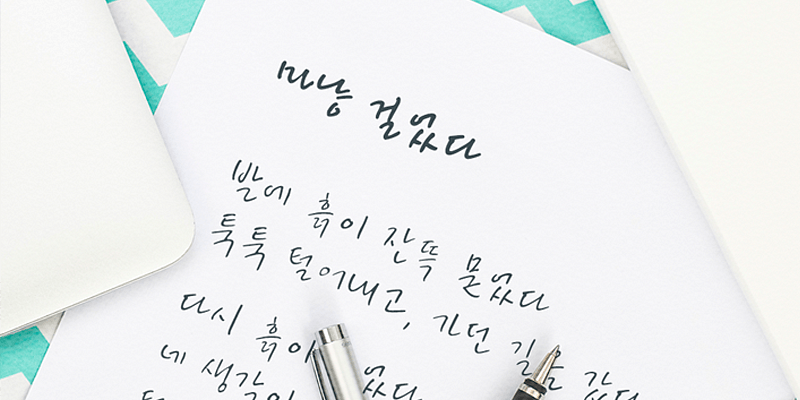
Sandoll 02는 자유롭고 캐주얼한 느낌을 주는 필기체입니다. DanA 글꼴로 유명한 손영희씨는 이 글꼴이 주는 자연 그대로의 감정을 강조합니다. 그리고 저녁이 되면 각 획의 두께로 자유분방한 느낌을 연출할 수 있습니다.
Sandoll(산돌)은 한국을 대표하는 글꼴 개발업체입니다. 약 40년 동안 거의 600개에 달하는 글꼴을 개발해 왔습니다. 이 개발업체는 한중일 개발, 한국어 및 기타 스크립트 매칭 등 다국어 프로젝트에 있어 다양한 경험을 보유하고 있습니다.